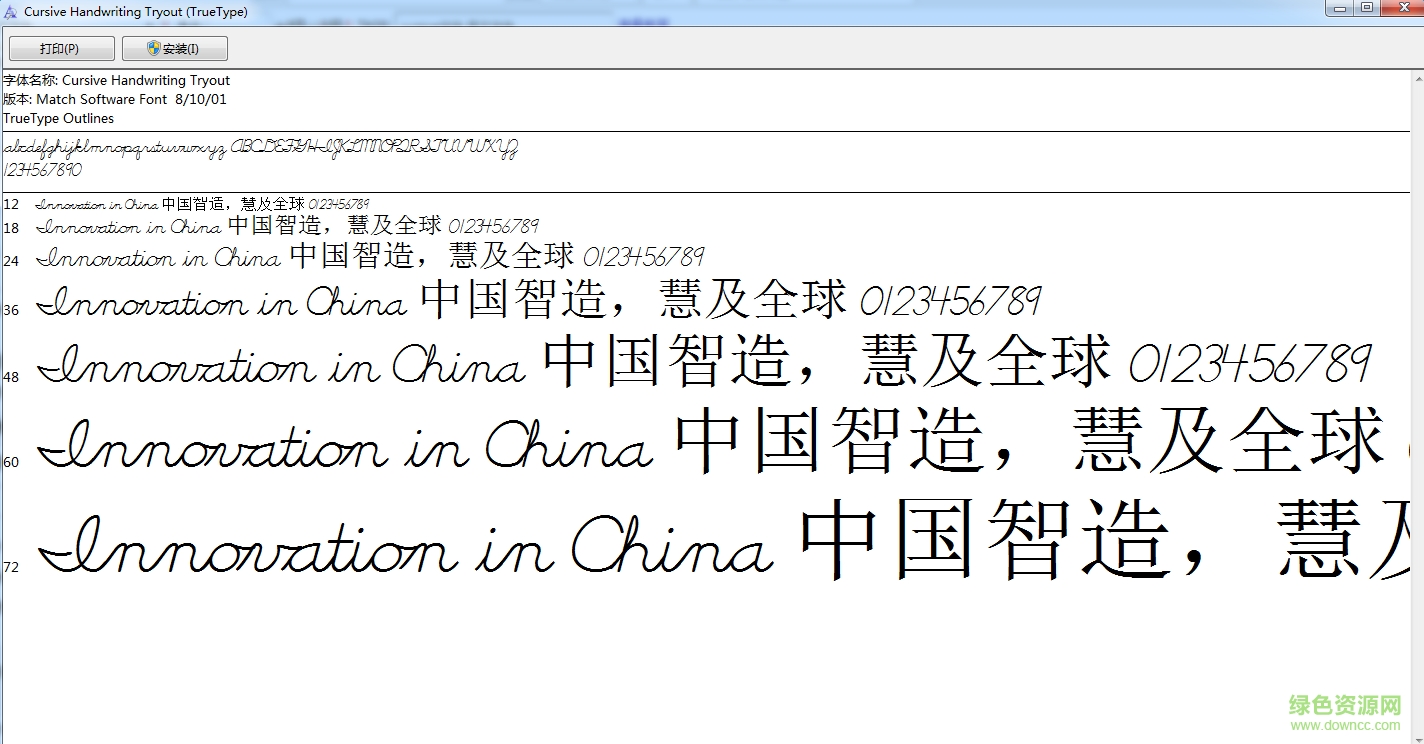
cursive字體是一款十分好看的英文手寫體,該字體筆畫連綿,線條靈動(dòng),筆形柔和,清新脫俗,喜歡的朋友歡迎在綠色資源網(wǎng)下載!
手寫體是一種使用硬筆或者軟筆純手工寫出的文字,這種手寫體文字,大小不一、形態(tài)各異,在計(jì)算機(jī)字庫中很難實(shí)現(xiàn)錯(cuò)落有致的效果。只能使用手工寫字的方法傳承下去。
cursive字體線條潦草,無拘無束,別有一番韻味,可用于書信設(shè)計(jì)、報(bào)告、文章以及美術(shù)設(shè)計(jì)方面!